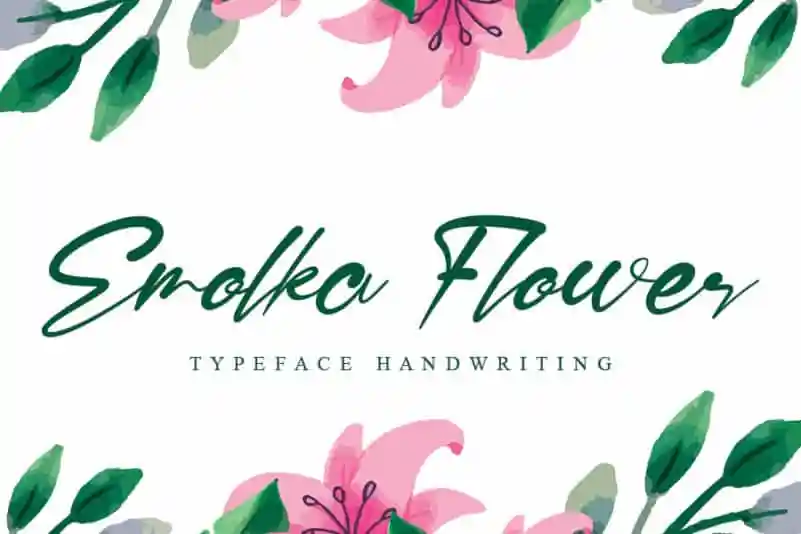
Emolka Flower Script Font é uma elegante fonte escrita a mão com fluidez, perfeitamente adaptada para projetos que buscam uma sensação natural e única. Seu estilo fluido e único faz dela uma opção perfeita para um vasto range de designs. O máximo que você pode alcançar é apenas sua imaginação. Estando disponível nas categorias de Fonts Handwritten, Emolka Flower Script Font se torna uma fonte irresistível para quem busca personalidade em seus projetos visuais. Com o Designer andikastudio responsável pela criação desta fantástica fonte, seu potencial criativo é limitado apenas pelo seu próprio imaginário. Descubra como Emolka Flower Script pode transformar suas ideias em obras de arte através do poder da escrita a mão.